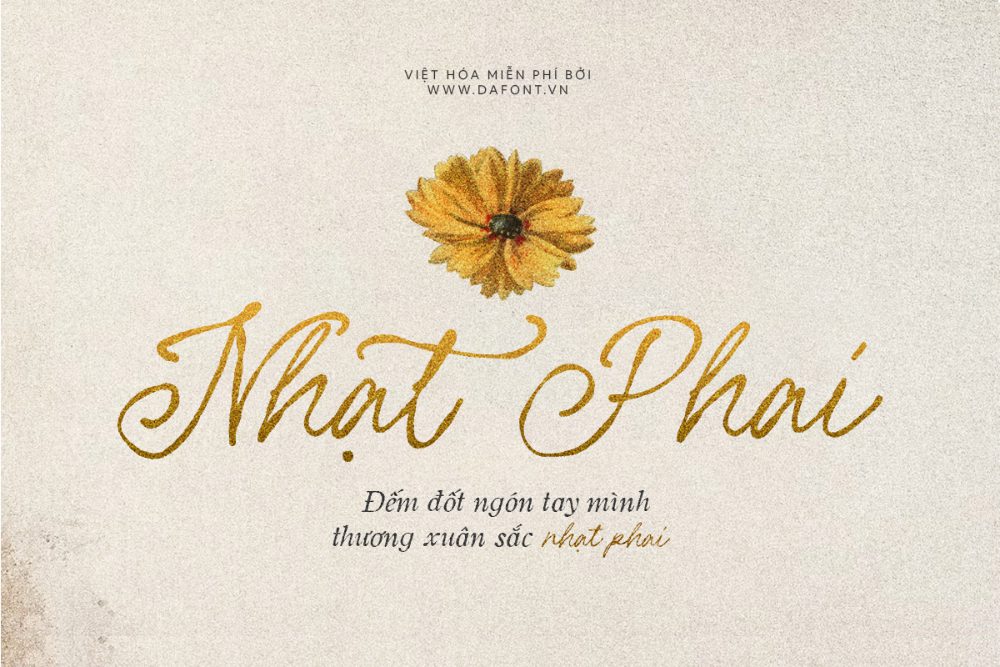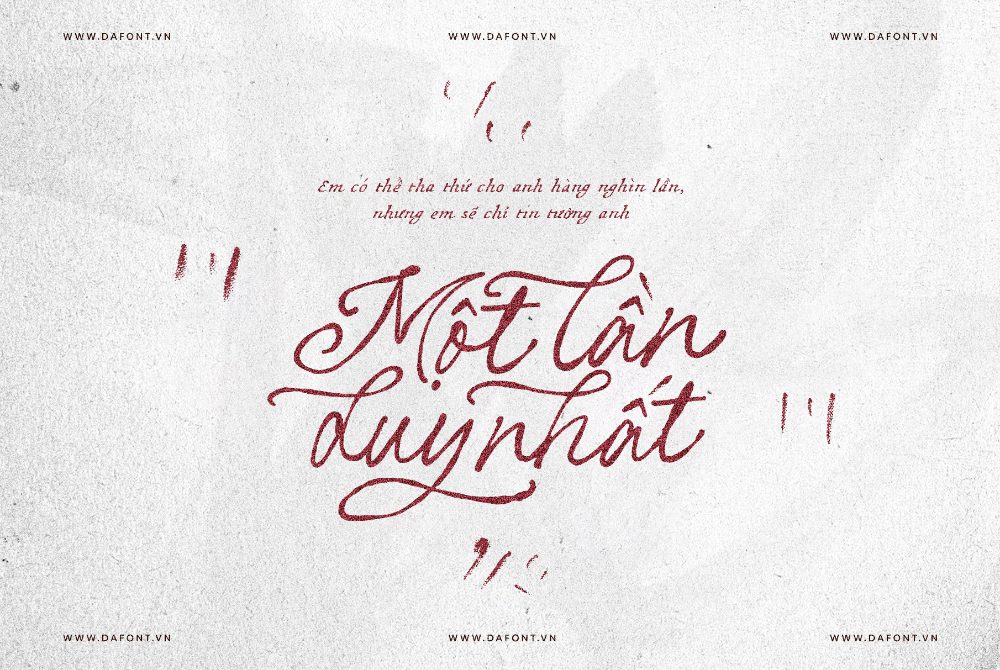
Tải Font Việt Hóa Les Palmiers là lựa chọn phù hợp dành cho những designer yêu thích phong cách chữ viết tay mang hơi hướng cổ điển, mềm mại và giàu cảm xúc. Trong thiết kế hiện đại, font chữ không chỉ đóng vai trò truyền tải nội dung mà còn góp phần tạo nên cá tính, cảm xúc và dấu ấn riêng cho từng sản phẩm. Với đường nét thanh thoát, tự nhiên và có phần nghệ thuật, Les Palmiers mang đến cảm giác hoài niệm, sang trọng nhưng vẫn gần gũi, rất thích hợp cho các dự án thiết kế cần sự tinh tế và khác biệt.
Font Les Palmiers Là Gì?
Les Palmiers là một kiểu font chữ viết tay có phong cách cổ điển, thường được sử dụng trong các thiết kế mang màu sắc vintage, retro, thủ công hoặc nghệ thuật. Điểm nổi bật của font nằm ở các nét chữ mềm mại, uyển chuyển, tạo cảm giác giống như chữ được viết bằng tay một cách tự nhiên.
Không giống những font sans-serif hiện đại có đường nét gọn gàng và tối giản, Les Palmiers tạo ấn tượng bằng sự bay bổng và cảm xúc. Font phù hợp với những thiết kế cần sự nhẹ nhàng, lãng mạn hoặc mang tinh thần hoài cổ. Khi được Việt hóa, font càng trở nên hữu ích hơn đối với designer Việt Nam vì có thể sử dụng đầy đủ dấu tiếng Việt trong các ấn phẩm truyền thông, thương hiệu hoặc nội dung sáng tạo.
Vì Sao Nên Chọn Font Les Palmiers Việt Hóa?
Hỗ trợ tiếng Việt đầy đủ
Một trong những lý do quan trọng khiến nhiều designer tìm kiếm Tải Font Việt Hóa là khả năng sử dụng tiếng Việt có dấu một cách chuẩn xác. Với các font chưa Việt hóa, tình trạng lỗi dấu, mất ký tự hoặc hiển thị không đồng bộ rất dễ xảy ra. Điều này ảnh hưởng trực tiếp đến chất lượng thiết kế, đặc biệt là các sản phẩm phục vụ khách hàng Việt Nam.
Font Les Palmiers Việt hóa giúp bạn dễ dàng sử dụng trong tiêu đề, slogan, poster, banner, thiệp mời, logo hoặc các thiết kế quảng bá mà không cần lo lắng về lỗi hiển thị. Đây là yếu tố rất quan trọng khi làm việc chuyên nghiệp, vì một font chữ đẹp nhưng lỗi tiếng Việt sẽ khó có thể ứng dụng hiệu quả.
Phong cách viết tay cổ điển cuốn hút
Les Palmiers mang vẻ đẹp của chữ viết tay cổ điển, vừa mềm mại vừa có cá tính riêng. Những đường cong tự nhiên trong từng ký tự giúp font trở nên nổi bật mà không quá cầu kỳ. Phong cách này đặc biệt phù hợp với các thiết kế cần tạo cảm giác gần gũi, tinh tế và giàu cảm xúc.
Bạn có thể sử dụng font cho các dự án như thiết kế thương hiệu cà phê, tiệm bánh, studio ảnh cưới, shop thời trang vintage, sản phẩm handmade, bao bì mỹ phẩm hoặc các mẫu poster nghệ thuật. Khi kết hợp với màu sắc trầm, texture giấy cũ hoặc hình ảnh mang phong cách retro, font Les Palmiers có thể giúp tổng thể thiết kế trở nên hài hòa và chuyên nghiệp hơn.
Ứng Dụng Của Font Les Palmiers Trong Thiết Kế
Thiết kế logo và nhận diện thương hiệu
Với phong cách chữ viết tay mềm mại, Les Palmiers rất phù hợp để tạo logo cho các thương hiệu cần sự tinh tế, nữ tính hoặc thủ công. Các thương hiệu trong lĩnh vực thời trang, làm đẹp, cà phê, bánh ngọt, handmade hoặc studio sáng tạo có thể tận dụng font này để xây dựng hình ảnh riêng biệt.
Một logo sử dụng font Les Palmiers thường mang cảm giác nhẹ nhàng, thân thiện nhưng vẫn có điểm nhấn. Tuy nhiên, khi dùng font viết tay cho logo, bạn nên cân nhắc độ dễ đọc và khoảng cách giữa các chữ để đảm bảo thương hiệu vẫn rõ ràng khi hiển thị ở nhiều kích thước khác nhau.
Thiết kế poster, banner và social media
Trong các thiết kế truyền thông, font Les Palmiers có thể dùng làm tiêu đề chính hoặc điểm nhấn cho bố cục. Nhờ nét chữ mềm và có chiều sâu, font giúp bài đăng mạng xã hội trở nên nổi bật hơn, nhất là những nội dung liên quan đến phong cách sống, thời trang, du lịch, nghệ thuật hoặc sản phẩm cao cấp.
Bạn có thể kết hợp Les Palmiers với một font phụ đơn giản như sans-serif hoặc serif tối giản để tạo sự cân bằng. Font viết tay nên được dùng vừa đủ, tránh lạm dụng toàn bộ nội dung vì có thể gây khó đọc nếu đoạn văn quá dài.
Thiết kế thiệp mời, menu và bao bì
Les Palmiers cũng là lựa chọn lý tưởng cho các thiết kế thiệp cưới, thiệp cảm ơn, menu quán cà phê, nhãn sản phẩm hoặc bao bì mang phong cách cổ điển. Những đường nét bay bổng của font giúp sản phẩm có cảm giác được chăm chút kỹ lưỡng, tạo thiện cảm với người xem.
Đặc biệt, với các thiết kế in ấn, font chữ viết tay cổ điển thường mang lại cảm giác cao cấp và thủ công hơn so với các kiểu chữ thông thường. Đây là lý do nhiều designer yêu thích sử dụng những font như Les Palmiers trong các dự án cần sự khác biệt.
Cách Kết Hợp Font Les Palmiers Hiệu Quả
Kết hợp với font đơn giản
Vì Les Palmiers có nhiều đường nét mềm mại và giàu tính trang trí, bạn nên kết hợp font này với các kiểu chữ đơn giản để tạo sự cân bằng. Ví dụ, dùng Les Palmiers cho tiêu đề chính và dùng font sans-serif dễ đọc cho phần mô tả, thông tin phụ hoặc nội dung dài.
Cách kết hợp này giúp thiết kế vừa có điểm nhấn nghệ thuật, vừa đảm bảo tính rõ ràng trong truyền tải thông tin. Đây là nguyên tắc cơ bản nhưng rất quan trọng khi sử dụng các font viết tay trong thiết kế chuyên nghiệp.
Dù sử dụng cho logo, poster, thiệp mời, banner mạng xã hội hay bao bì sản phẩm, font Les Palmiers đều mang lại nét đẹp riêng nếu được kết hợp đúng cách. Hãy lựa chọn bố cục hợp lý, phối màu tinh tế và dùng font ở vị trí phù hợp để phát huy tối đa vẻ đẹp của kiểu chữ viết tay cổ điển này.